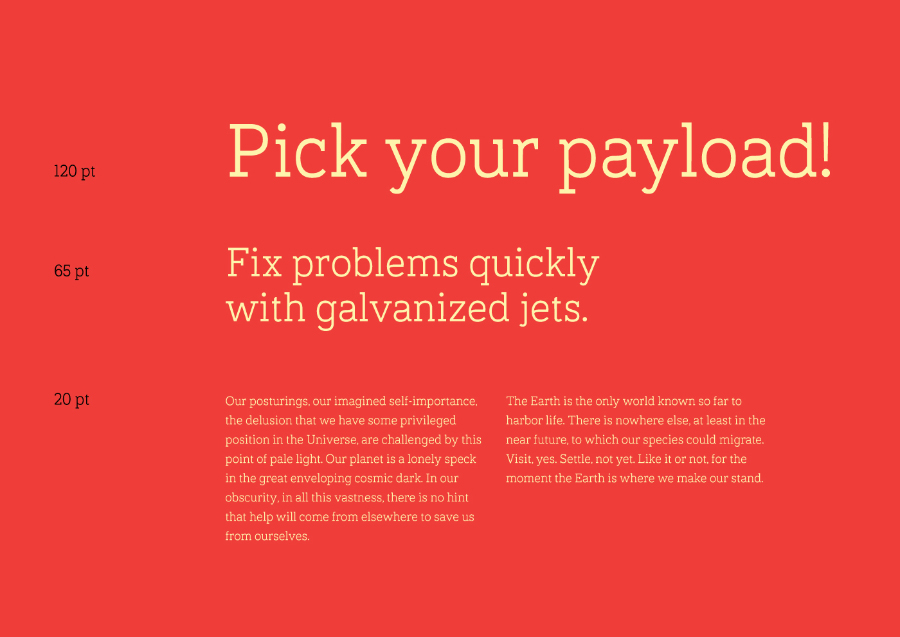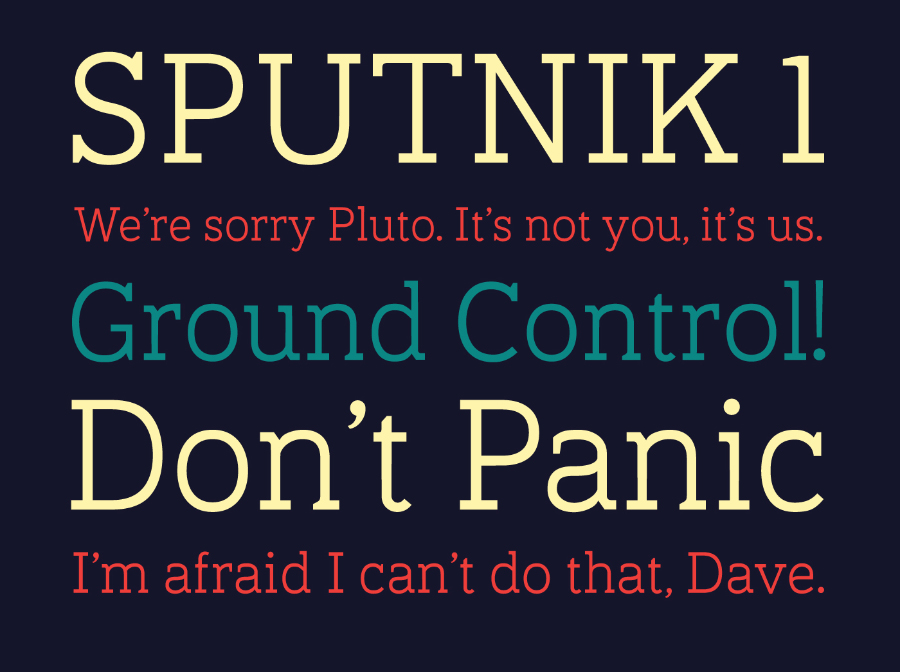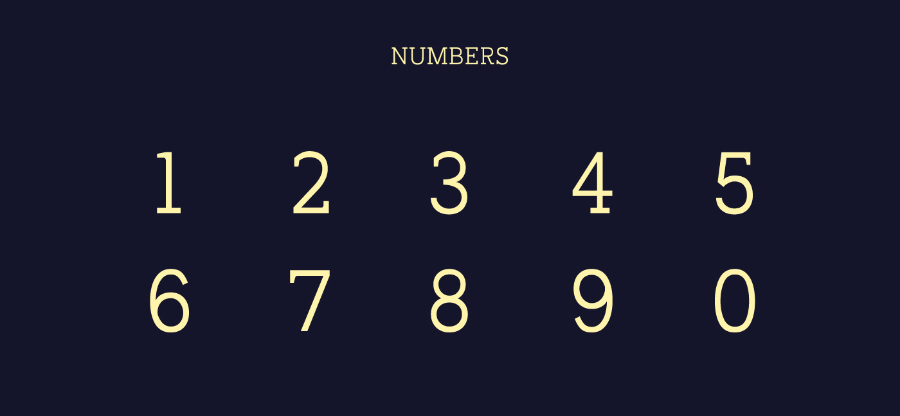
Saros Slab Serif Free Font
Saros Slab Serif Free Font是一个灵活的字体,旨在为打印和屏幕上的类型提供可靠性和个性。它在尺寸上被构造,以非常小的尺寸在显示器尺寸和一致的可读性上提供醒目的形式。所以萨罗斯可以用于很多目的非常有用。它会看起来不错,如标题,标志或品牌,海报和横幅。但是它也开放了正文,书本和其他小型的介绍。现在得到它是免费的!